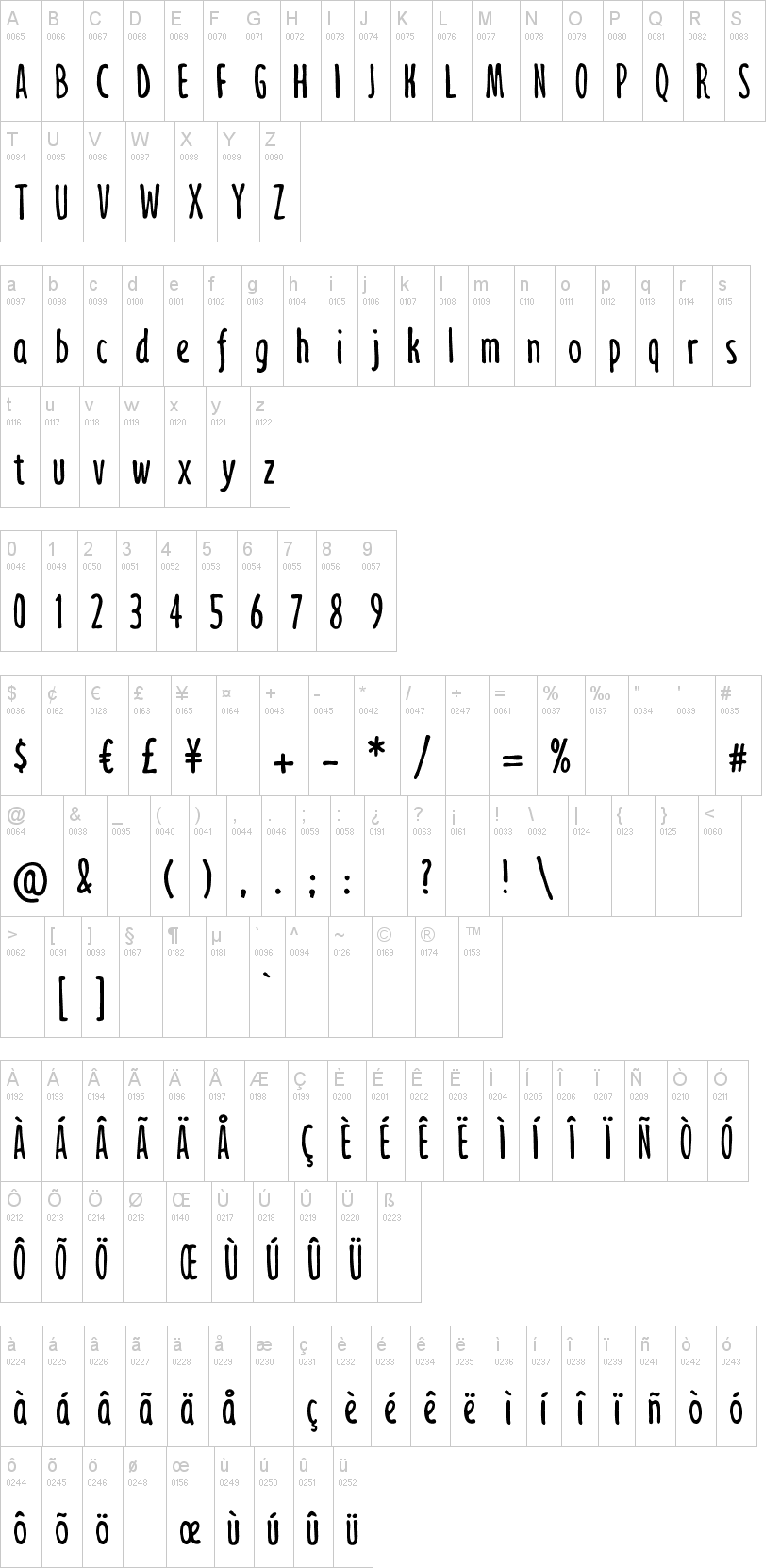
Jollysight Sans 字体是一种现代且具有创新性的无衬线字体,由 JollyGood Type 设计。该字体设计师从视觉形状、比例、间距和颜色等多个方面考虑,呈现出一种均衡美感和和谐感。字母的线条流畅简洁,具有可读性和易用性,适合在多种应用场景中使用,包括印刷和数字媒体。 Jollysight Sans 字体目前提供了 6 中字重,从常规到黑体的选择,可以满足不同设计需求。这种字体还具有一些特殊的设计元素,比如圆形的字母 g 和单层的字母 a,增强了视觉的个性化和独特性。 总之,Jollysight Sans 字体具有现代感和科技感,适用于各种设计场景,是一种优秀的字体选择。内容介绍
Jollysight Sans是一款非常不错的手写艺术字体,具有很好的视觉感,适合于文化类的宣传设计、商业类品牌的广告和产品包装设计以及个性化文字排版等较多场景。